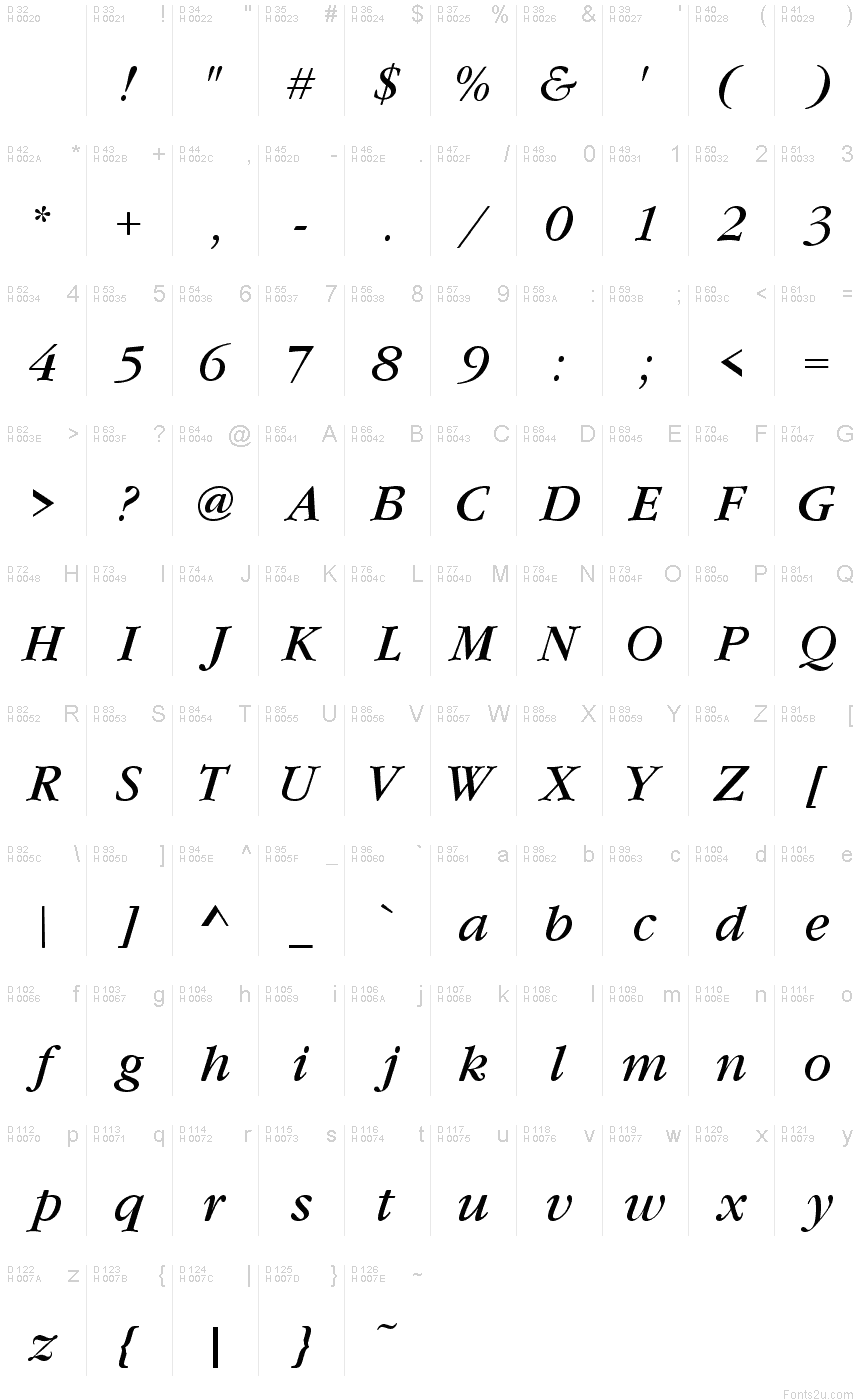
Gourmand  Italic
Gourmand Italic di MGI Software è un carattere serif calligrafico gratuito che scorre sulla pagina come una ganache al cioccolato. Le sue curve ampie, l'inclinazione generosa e i tratti vellutati infondono in ogni parola un senso di piacere e dinamismo, come se fosse stata scritta con un pennino largo e inchiostrato. È presente anche un sottile fascino vintage, che rende Gourmand un carattere tanto lussuoso quanto accogliente.
Questo font gratuito è perfetto per loghi di ristoranti, etichette di vini, titoli di menu, packaging gastronomico, copertine di libri di cucina, blog di ricette e inviti a eventi. Usa Gourmand Italic in dimensioni più grandi per far risaltare le sue forme fluide; abbinalo a un carattere sans serif pulito per il testo principale per garantire leggibilità e raffinatezza.